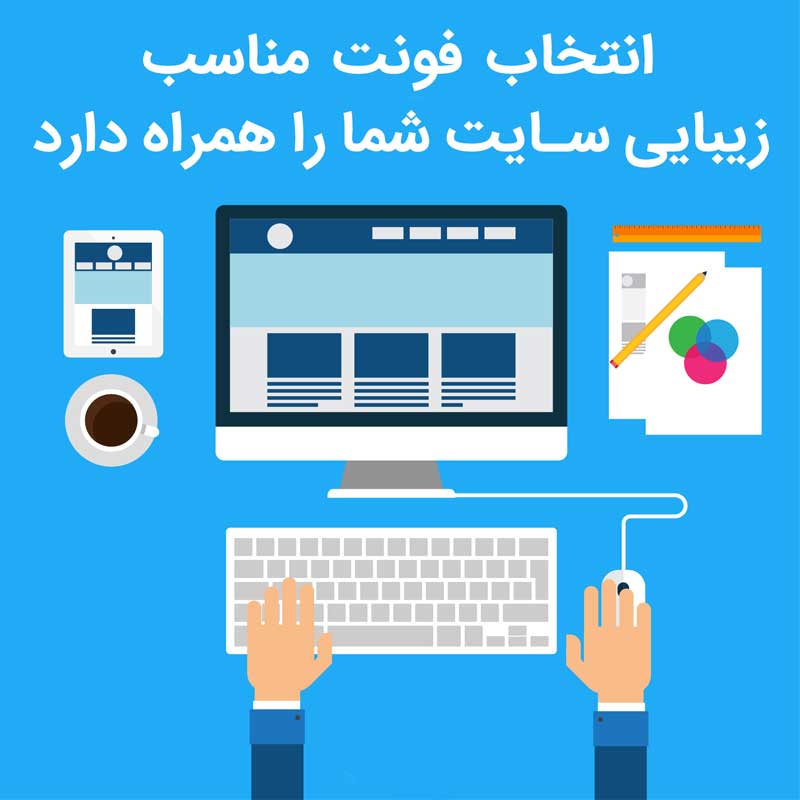
دلیل اهمیت فونت‌ها در طراحی سایت چیست ؟
اهمیت فونت ها در طراحی سایت به چه منظوری است؟ از چه font هایی باید استفاده کنیم؟ آیا تاثیری در سرعت لود شدن صفحه دارند؟
فونت ها در طراحی سایت از اهمیت بالایی برخوردارمی باشند.  در واقع آن ها  لباسی هستند که یک وبسایت به تن می‌کند و اینکه یک وبسایت از دید ناظر که همان کاربر است چگونه به چشم می‌آید، فارغ از اینکه چه توانایی‌هایی دارد، بسیار مهم است. شخصیت، پرستیژ و قدرت یک سایت در گرو احساسی‌ است که به کاربر منتقل می‌کند و فونت ها جز مواردی هستند که به بیشترین مقدار در معرض دید هستند. انتخاب فونت درست می‌تواند پیام شما را پیش از آنکه مخاطب نوشته‌ های شما را بخواند به او القا کند.
جزئیات کوچک در طراحی آن ها تاثیرات متفاوتی بر ذهن خواننده می‌گذارد؛ مثلا استفاده از فونت‌های کتابی باعث ایجاد حس اعتماد و استفاده از فونت های مدرن که خطوطی نازک‌تر و زوایایی گردتر دارند باعث ایجاد نوآوری و پیشرفتگی در کاربر می‌شود. اگر به دنبال طراحی یک سایت زیبا و اصولی هستید این قسمت از آموزش طراحی سایت را دنبال کنید
انتخاب فونت مناسب به سایت شما جذابیت می بخشد
برای انتخاب فونت مناسب باید به چه نکاتی توجه کنیم؟
برای انتخاب فونت مناسب عوامل زیادی برای درنظر گرفتن وجود دارد، اما سعی خواهیم کرد شما را با اصلی‌ترین نکات آشنا کنیم.
-همخوانی با اهداف
اولین نکته‌ای که برای انتخاب فونت باید در نظر گرفت این است که آیا ظاهری که در سایت ایجاد خواهد شد با اهداف تجارت و برند من همخوانی دارد؟ برای مثال شما هیچوقت نمی‌توانید کاربران یک سایت دانشگاهی را با فونت‌های فانتزی راضی کنید.
-ثبات
این را در نظر داشته باشید که یک سایت در دستگاه های مختلفی از موبایل و ساعت هوشمند گرفته تا لپ تاب و تلوزیون دیده می‌شود. پس باید فونتی را انتخاب کنید که بتواند ثبات ظاهری را در همه حفظ کند و همه‌جا خوانا به نظر بیاید.
-عملکرد فنی
یکی از مهمترین و اصلی‌ترین المان های طراحی سایت، سرعت لود صفحات است. خیلی وقت‌ها انتخاب یک فونت اشتباه می‌تواند به سرعت لود صفحات سایت صدمه بزند.
-دسترسی عمومی
فونت هایی که تحت عنوان Web Font  شناخته می‌شوند، در دسترس همه کاربران اینترنت قرار دارند اما سایر فونت‌ها لزوما در سیستم همه بازدیدکنندگان وجود ندارد و انتخاب فونتی بیش از حد شخصی می‌تواند تمام زحمات شما را برای طراحی استایل زیبا در سایت هدر دهد.
-همه کاره بودن
در نظر داشته باشید که در حال نوشتن مقاله‌ای هستید و نیاز است تا به خواننده القا کنید که بخش‌هایی از مقاله اهمیت بیشتری نسبت به سایر مطالب دارند. اگر فونت شما امکان تغییر حالت نداشته باشد چگونه این کار را انجام خواهید داد؟ امکاناتی مثل Bold  و italic و به طور کلی قابلیت ‌های فونت باعث می‌‌شوند تا بتوان ارتباط بهتری با مخاطبان برقرار کرد.
-رتبه در موتورهای جستجو
برخی از طراحان حاضرند به خاطر ایجاد ظاهری زیبا، نوشته های سایت را تبدیل به عکس کنند تا نمای ظاهری آن را حفظ کنند. این کار باعث می‌شود تا موتورهای جستجو و به طور دقیق‌تر خزنده‌ها نتوانند مطالب شما را مطالعه کنند که این کار باعث افت شدید رتبه سایت خواهد شد.